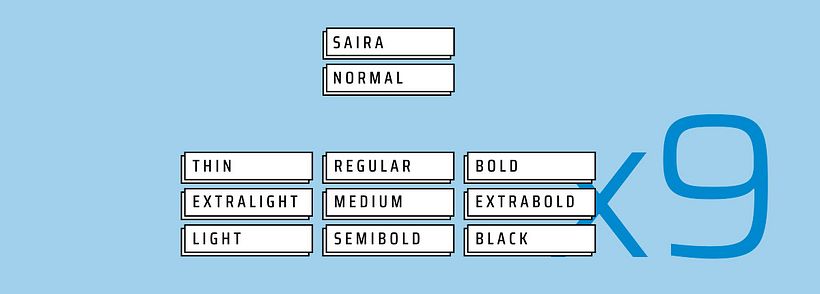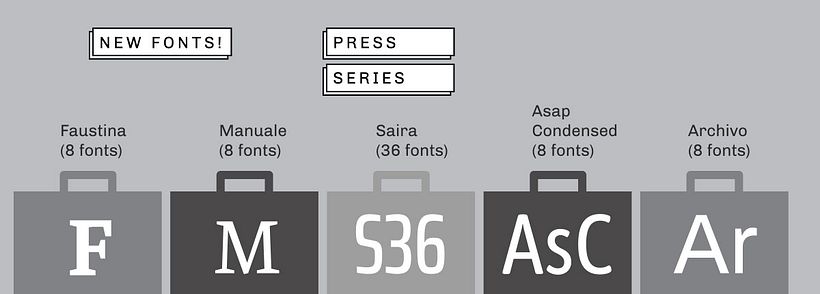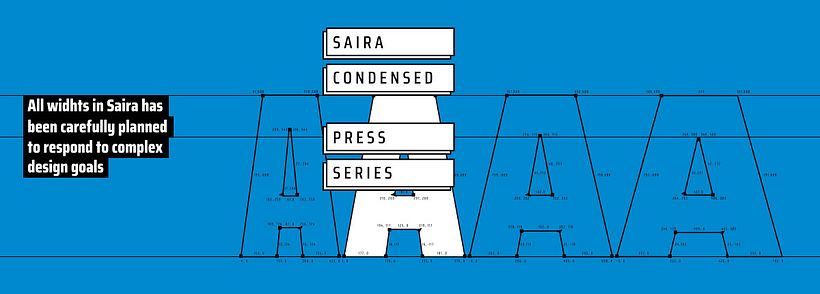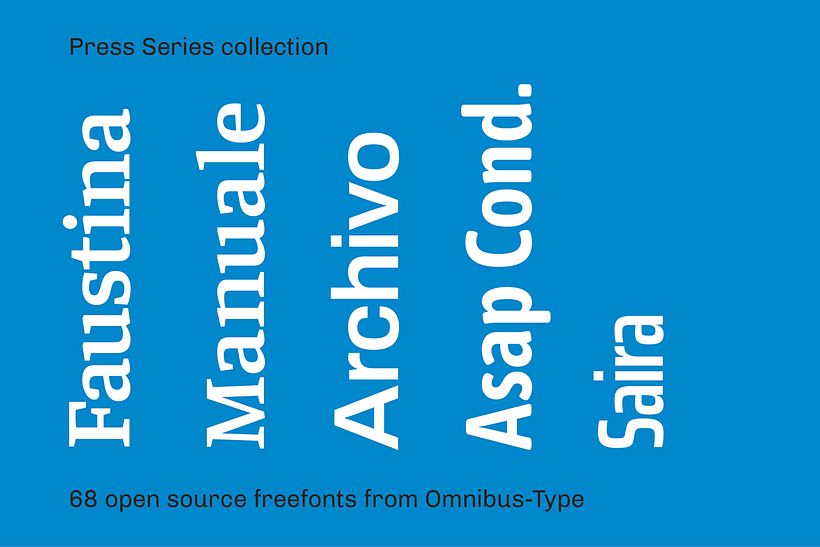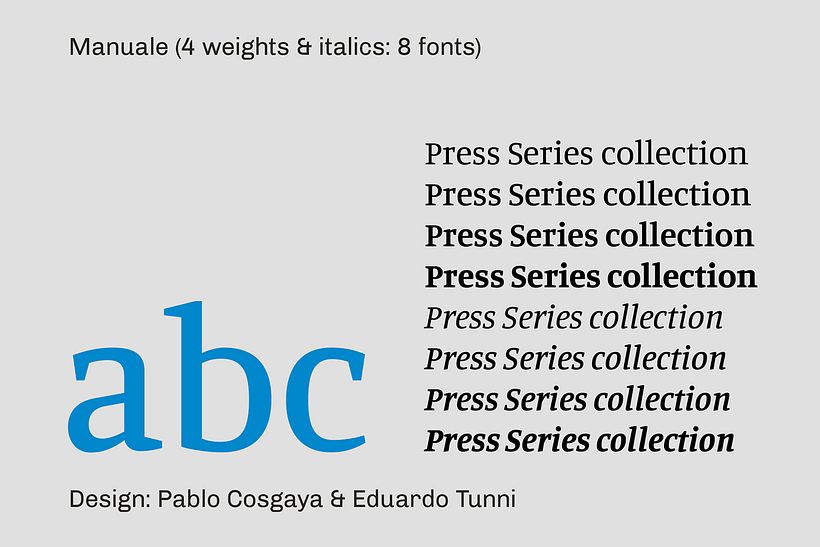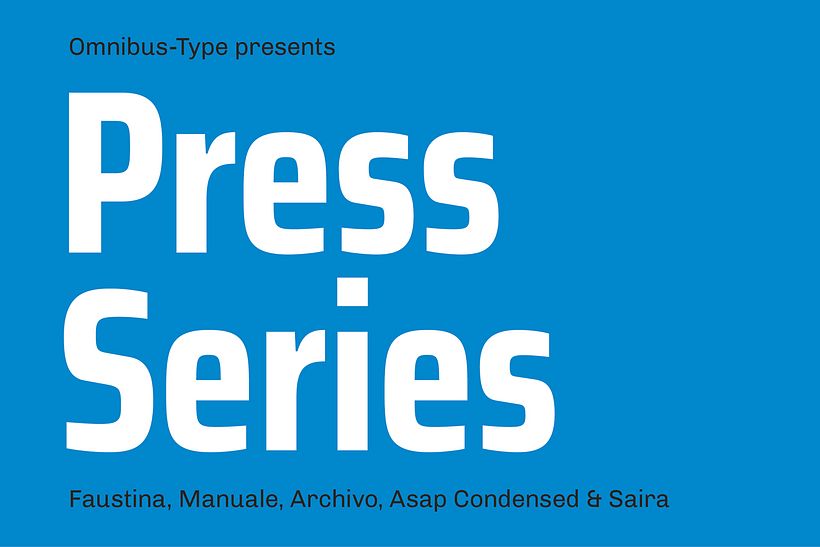
Press Series, las tipografías libres de Omnibus-Type
La fundición digital argentina Omnibus-Type comparte libremente sus tipografías para usar en cualquier proyecto.
Press Series es, ni más ni menos, uno de los últimos proyectos que la fundición digital argentina Omnibus-Type tiene entre manos. Se trata de cinco familias tipográficas, especialmente diseñadas para facilitar la lectura de publicaciones impresas y digitales, que comparten de manera gratuita y con libertad de uso para cualquier tipo de proyecto, a través de Google Fonts.
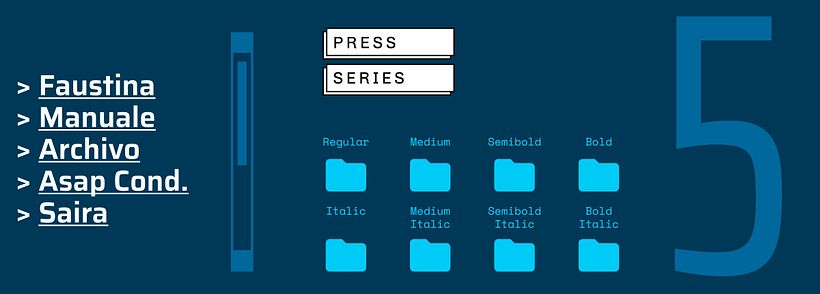
Faustina y Manuale, dos tipografías con serifa y generoso ojo medio, son las reinas de la corona de esta colección, aunque comparten protagonismo con Archivo Narrow y Asap, las tipografías más populares de la fundidora –y también las que más veces se han descargado de entre todas las de esta selección– y con Saira, pensada para reinar en los titulares.
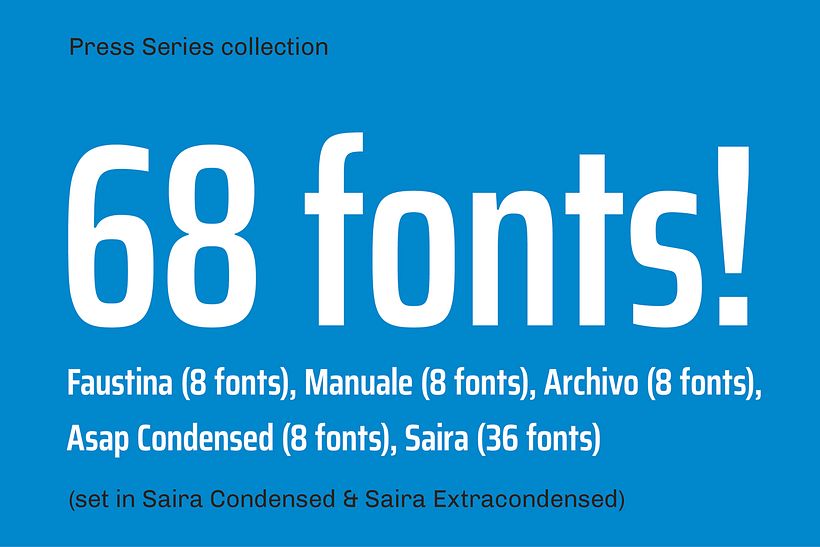
La colección Press Series aglutina, en total, 68 fuentes compuestas por cinco familias tipográficas de gran calidad creadas por Onmibus-Type.